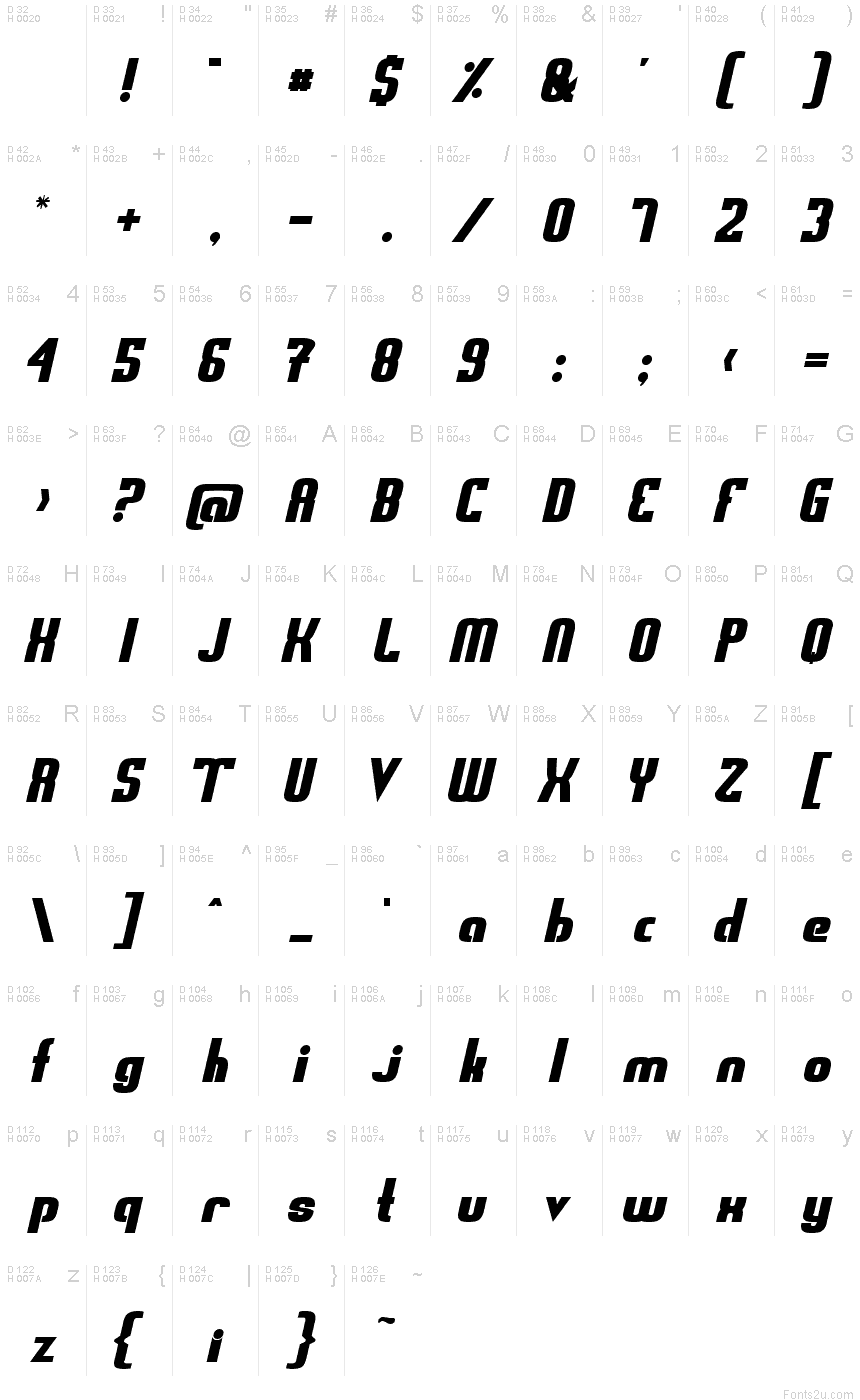
Sweden Funkis RegularOblique
Sweden Funkis autorstwa Samuela Parka to darmowy, utrzymany w stylistyce groovy font typu display, który przenosi nas w klimat skandynawskiego lounge’u lat 70. Litery pochylają się w płynnym ruchu, a ich masywne, zaokrąglone kształty, nisko osadzone łuki i miękkie łączenia sprawiają, że napis wygląda, jakby został odlany, a nie narysowany.
Font świetnie sprawdzi się na plakatach muzycznych, w identyfikacji retro kawiarni, na okładkach płyt, w grafikach festiwalowych czy dużych nagłówkach redakcyjnych, gdzie sam krój pisma potrafi zbudować cały klimat. Wykorzystaj go również w krótkich tytułach i logotypach – dzięki nachyleniu i miękkiemu rytmowi nadaje on nawet pojedynczym słowom luźny, funkujący charakter.